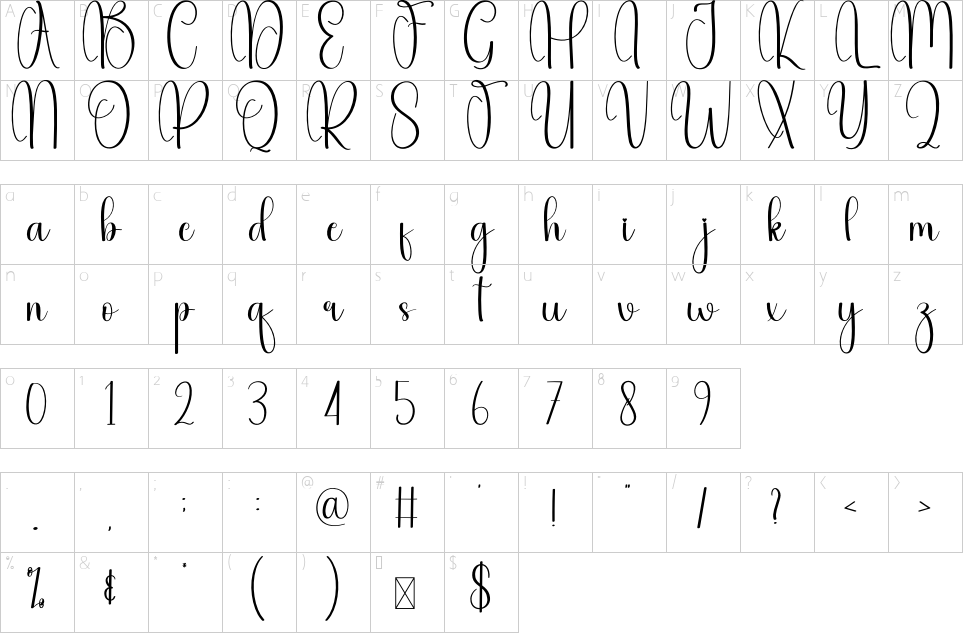
A Mansion Font oferece um charme único e elegante para designers de jogos, publicidade e sites, apresentando linhas elegantes e um contraste interessante entre as letras mais finas e as mais grossas. Ela foi projetada por alguém chamado William Jhordy e tem sido baixada mais de 415 vezes. Seja para criar gráficos profissionais ou para adicionar um toque único a um site, a Mansion Font é uma excelente escolha para quem valoriza uma fonte elegante e sofisticada. Com essa fonte, você pode garantir um design de qualidade, que vai atrair a atenção do seu público-alvo. Não importa se você está criando para dispositivos Windows ou Mac, a Mansion Font tem o que você precisa. Com certeza, ela será uma fonte excelente para seu próximo projeto.